你对中华文化的理解可能还不如这个外国人
我们在不久之前介绍了靳埭强,我们称靳埭强为“香港第一代华人设计师”,不知道大家有没有想过为什么在设计师前面加了“华人”两个字呢?没错,那是因为“香港第一代设计师”另有其人,那就是被称作“香港设计之父”的石汉瑞。虽然有着中国名字,可是石汉瑞却是一名地地道道的美籍犹太人。
石汉瑞
香港平面设计之父。将西方现代平面设计带到香港,对香港甚至中国的平面设计发展有不可磨灭的贡献。
大师的背后,是一群大师
石汉瑞于1934年2月13日出生于奥地利巴登的一户犹太家庭。为了躲避二战战祸,石汉瑞5岁的时候全家移民到了美国纽约。1995年,他在纽约亨特学院完成了绘画艺术专业的学业后,进入了耶鲁大学平面设计系修读硕士学位。
左:保罗兰德 右:石汉瑞
在纽约学习的这段时间,石汉瑞跟随过多名著名的艺术家、设计师,其中包括了抽象表现主义画家罗伯特·马瑟韦尔、威廉·巴泽蒂斯、雕塑家理查德·利波尔德、国际达达主义领袖等等,当然还有影响他一生的导师保罗·兰德(Paul Rand),可以说是集万千宠爱于一身了(我流下了羡慕的泪水)。
1985年,石汉瑞获得了富尔泰布莱特奖学金,并前往巴黎索邦大学继续学习深造。去了巴黎之后,石汉瑞发现索邦大学的课程并不完善,于是石汉瑞便自己去寻找一些学习的机会,例如找一些自由设计的工作,以及跟随巴黎的设计大师雷蒙德·萨维尼亚克工作学习(害!又是一位大师)。在巴黎的这段时期,虽然对石汉瑞的设计水平上并没有太大的帮助,但却深深丰富了他的人生阅历,让他成为独立、思想全球化的人,为他打开了国际化的新世界大门。
寻寻觅觅,
最终在香港扎下了根
1961年,石汉瑞就接到了《亚洲周刊》的邀请,来到香港,担任《亚洲周刊》的设计总监,原本只是为期9个月的短期工作,这一呆就呆到了现在。4年之后,30岁的石汉瑞创办了自己的设计公司——品国语设计有限公司(现是石汉瑞设计公司),以企业形象设计为主要业务,石汉瑞应该算得上是香港最早推广企业形象的人。
石汉瑞刚到香港的时候,香港还没有形成真正意义上的“现代设计”,市场上的商业设计都是由画家兼职创作的商业美术插画和美术字。也许是时代造英雄吧,石汉瑞创办的公司几乎不需要宣传,生意便源源不断的通过人际关系网络送上门,也正因如此,品牌与平面设计的概念也通过这一桩桩的生意传播开来了。可以说石汉瑞的到来,也将瑞士国际平面主义设计风格和纽约的平面设计派带到了香港,促使了西方现代设计在香港落地生根。因此,石汉瑞也被称为“香港的平面设计之父”。
那么是什么促使了石汉瑞留在了香港,尽管后来香港的设计行业陷入了低迷?原因大概有两个,其一是石汉瑞认为香港自由且舒适,并且嗅到了来自香港和大陆的巨大商机。其二是石汉瑞被香港这种中西方文化互相冲击交融的环境深深吸引着,这种跨文化的氛围总能给他源源不断的灵感。
中庸之道,中和之美
《中庸》是儒家思想的核心,可以理解为不偏不倚的中和圆满。如果用设计的角度来理解的话,就是将画面中各种元素和谐的放在一起,但是却不丧失他们各自独特的美。好吧,说人话就是存在对比的同时,画面也要保持平衡稳定。在石汉瑞的设计中,对比是一直被强调的,无论是形式上还是他想表达的内涵上。石汉瑞最牛逼的一点是,他始终能抓住不同文化之间的共性和个性,并且使他们很好的结合在一个画面中。这一点和《中庸》的思想就不谋而合了。
1989年,石汉瑞做过一张叫做《自画像》的海报,这张海报就充分地表现了他对“中和之美”的追求。这张海报由一张摄影照片和四张他自己的作品组成。墙上的三件作品分别是1980年为汇丰银行设计的年报封面,1986年应邀创作主题为“序列”的海报《筷子》和1969年为“香港国际音乐节”设计的海报,从这三个海报中都可以看出石汉瑞跨文化设计的特色。
我们主要来看看这张被当做背景的照片。这张照片记录了清代画家关乔昌(当时西方称他为林呱)正在作画的场景。林呱虽然是中国画家,但是却专职画油画。当时在广州像林呱一样的画家非常多,经过西方画家的指导,使用西方的绘画工具,将中国社会风貌与风景画下来并卖给来广州的外国人。他们这一批画家虽然用的是西方的工具和绘画技巧,可是依旧保持着中国传统的执笔方式和散点透视方法。这样结合东西方绘画技巧的尝试,也可以算得上是早期中西方文化结合的一个缩影。石汉瑞借用林呱这样的一个创作场景,一方面表达了自己对多元文化的包容和多元文化对自己创作的影响,另一方面也是表达了对那些早期跨越文化障碍,从事艺术创作的先辈们的敬意。
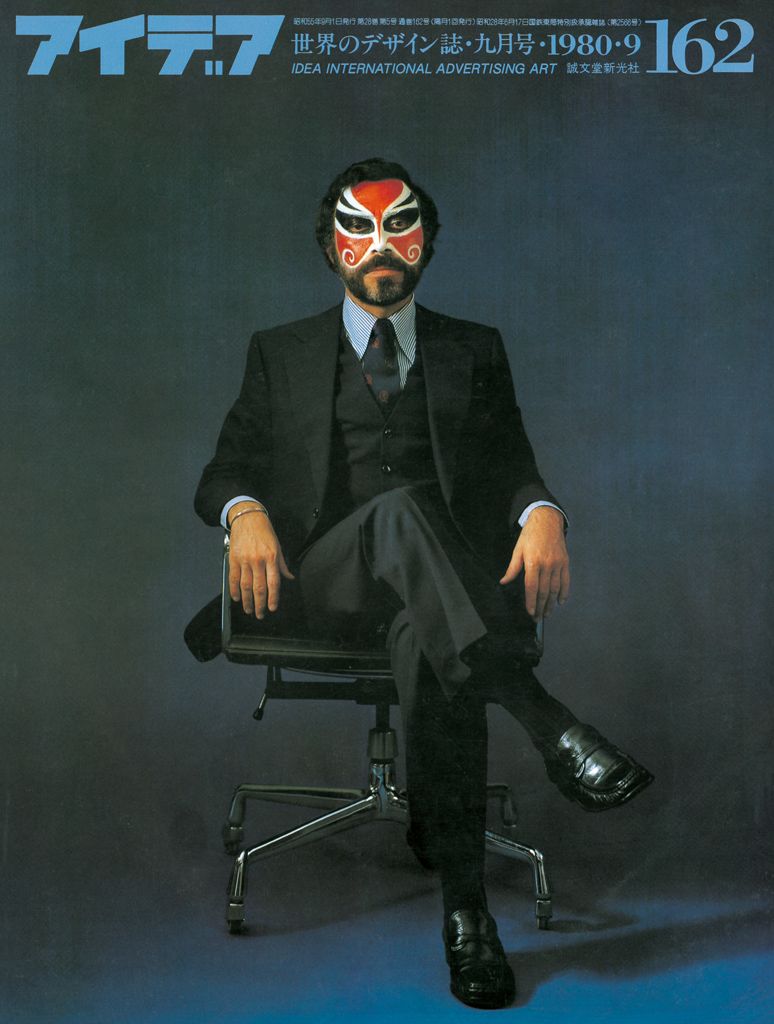
另外被石汉瑞放在林呱正在作画的画板上的那件作品其实也特别有意思。这是石汉瑞设计的一期《IDEA》杂志的封面,这个封面上是他西装革履地坐在一张椅子上,可是脸上却画着一张京剧的脸谱。这个设计本身就蛮有“自画像”的意味,作为一个外国人的他远渡重洋来到香港从事设计工作,面对的客户有中国人也有外国人,在这样一个多元的文化环境中工作,正如画着京剧脸谱的他,体现了他对多元文化的包容。
其实石汉瑞这种“中和一切”的能力到了现在也非常的值得我们学习。张亚东在《圆桌派》中说过现在是一个拼贴的时代,其实我觉得音乐和设计一样,对设计来讲这同样是一个拼贴的时代,没有什么是不能够放在一起的,只要能将两个或者是多个不同的东西巧妙地“中和”在一起,那么就是一个好的创意。可是到底应该怎么样“中和”呢?这就是值得我们去探究和学习的地方,下面我们来看看石汉瑞是怎么“中和”一切的?
图像的中和
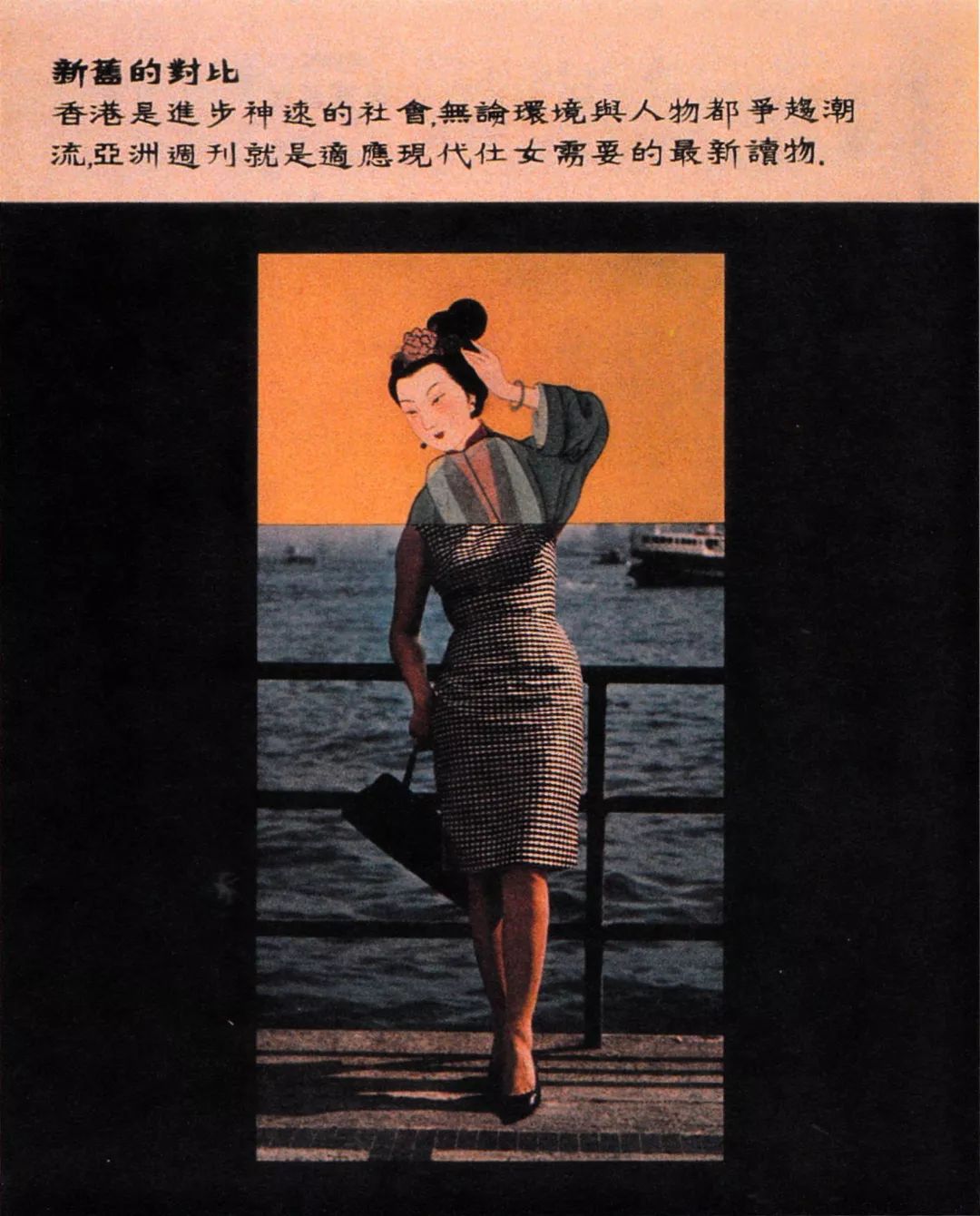
1964年,《亚洲周刊》为了想突出杂志的前卫和新颖,设定了一个“新旧的对比”主题。石汉瑞用两个完全不同的女性上下组合而成的一个新形象作为主体画面。一个是古代的仕女,一个是背对着香港天星码头的现代摩登女性,通过古与今的两位女士作对比,来强调“新旧的对比”。另外从面积上看,上面的古代仕女所占的面积小于下面的现代女性,从而突出强调“新”的力量。虽然是机械的切割,但是通过位置和大小的合理摆放,使得新形象看上去自然、协调,没有违和感。
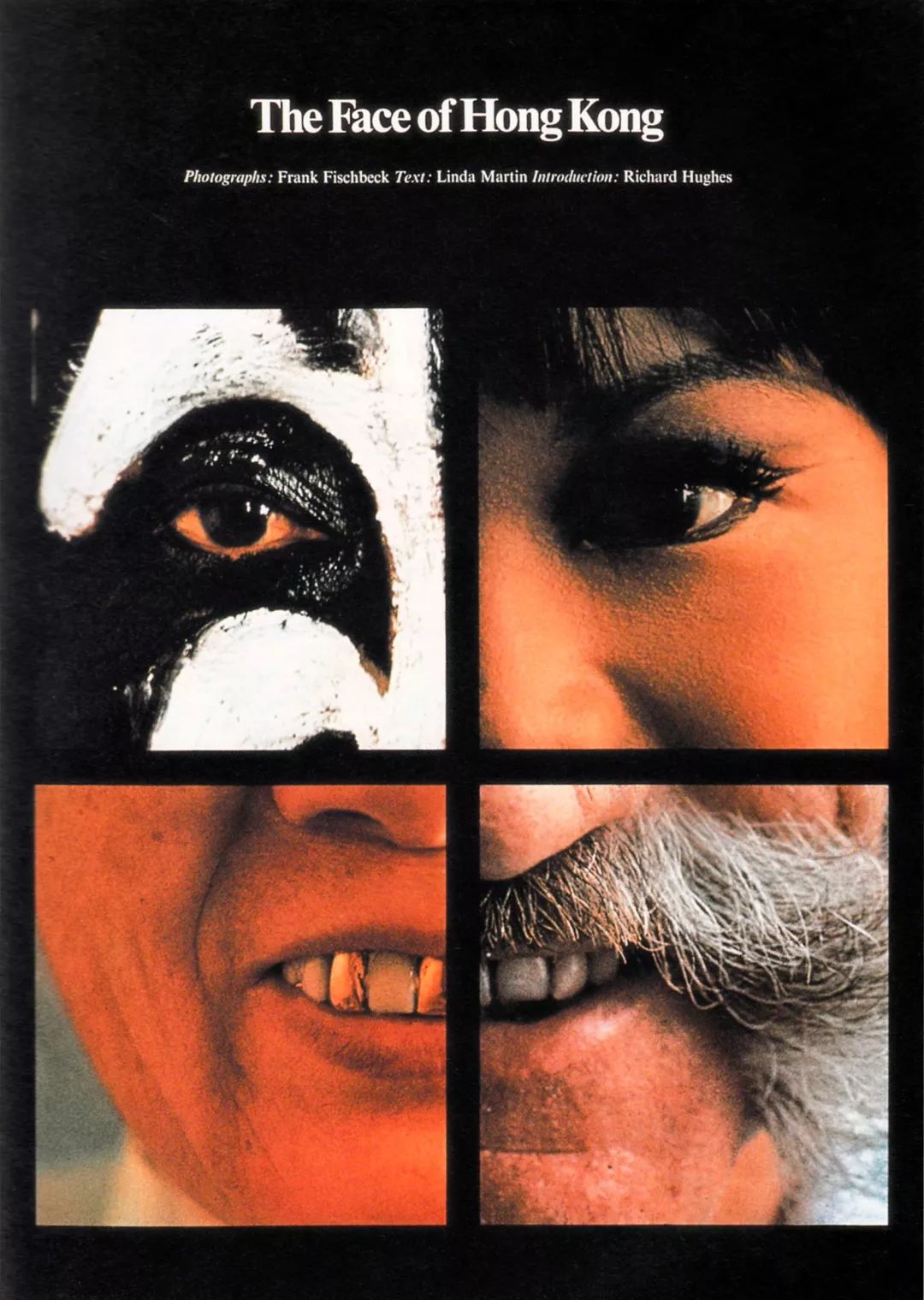
《香港面貌》是一本展现香港人面貌的摄影画册,画册里呈现了28组不同人物的肖像摄影,不同年龄不同职业,每一组人物形象都代表着香港生活的一个方面。石汉瑞在设计这个画册封面的时候,选取了4个身份不同的人物肖像,分别是粤剧演员、酒吧女郎、镶了金牙的阿嫲和在天星码头工作的外国人,各取其脸部形象的四分之一然后重新组合成一张新的面孔。这个设计一方面与画册展示人物肖像的主题相呼应,另一方面也简洁明了地将香港多元文化共处的特点表达了出来。
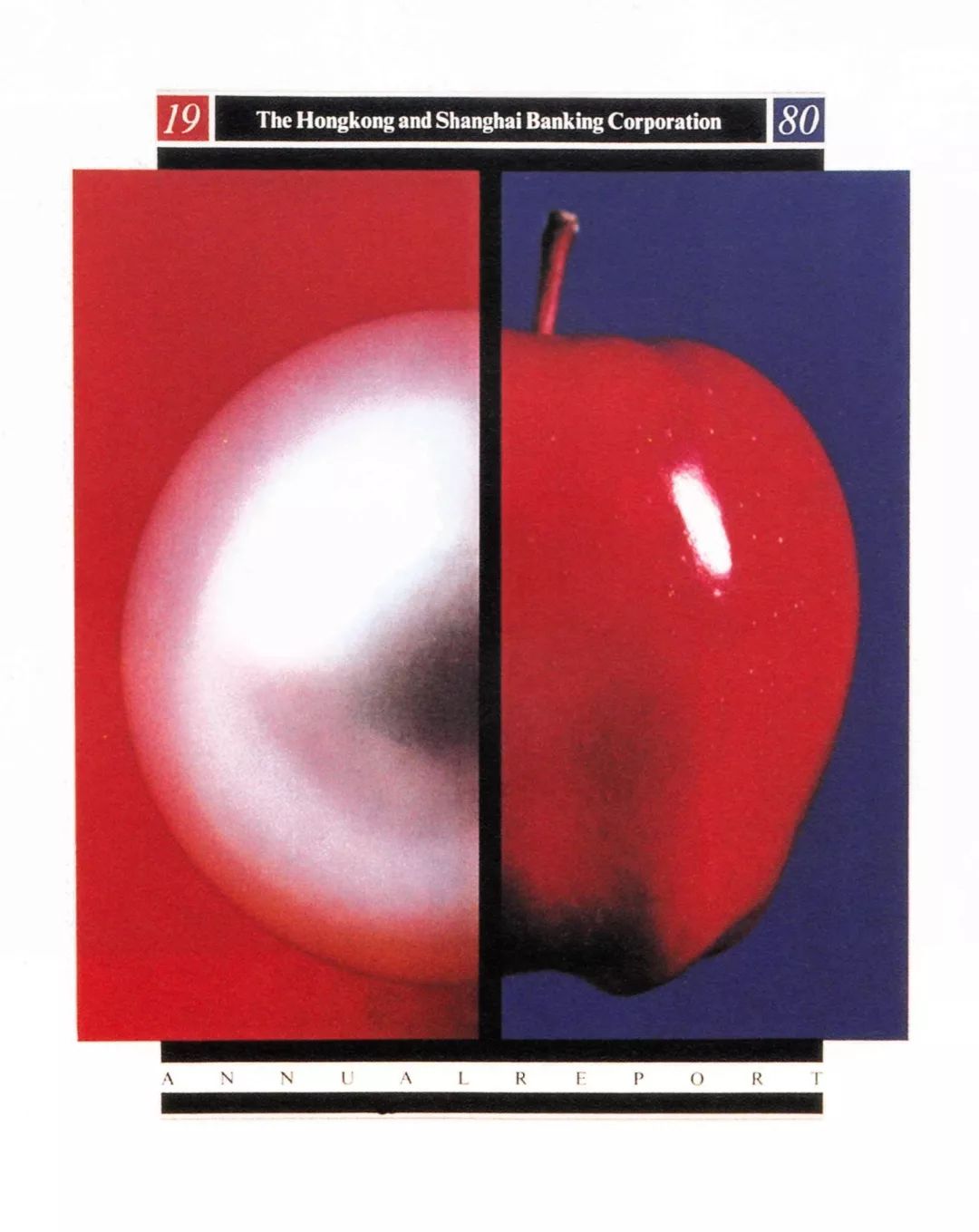
1980年,石汉瑞为汇丰银行纽约分部成立100周年设计年报,在年报的封面中,石汉瑞同样使用了图像分割再重新组合的手法。石汉瑞选用了珍珠代表被称作“东方明珠”的香港,选用苹果代表“The Big Apple”纽约。各取左右一半并置在一起,表明了香港汇丰银行和纽约分部的隶属关系。
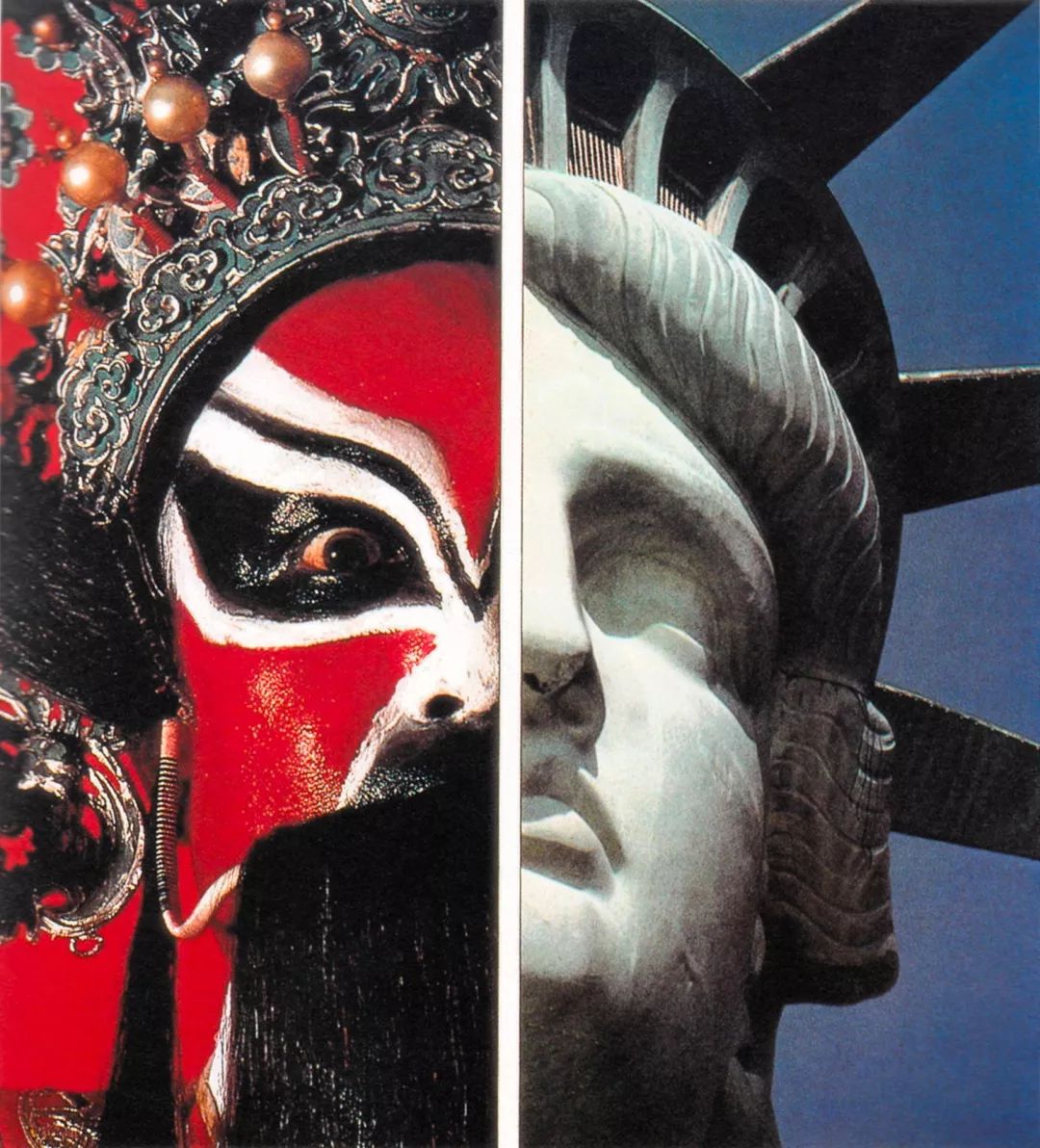
在该年报的内页中也有一页用了相同的方法,将粤剧的人物形象与纽约自由女神像各取一半然后并置一起。20世纪80年代是香港经济飞速发展的时期,将香港和纽约放在一起,体现了汇丰银行全球化扩张的战略和预示着香港的发展前景。
文字的中和
为了突出《亚洲周刊》的前卫与新颖,石汉瑞为其做了一个不同文字进行对比的海报。画面的主体由红色的黑体字“新”和绿色的书法字“旧”组成,这两个字被45°斜线切割去掉了一半,然后并置在了一起。石汉瑞直接用文字的字义来表达“新”与“旧”的对比。另外,黑体字相较于传统书法字也算是新式的,黑体字机械整齐的线条与飘逸灵动的书法字也形成了视觉上的强烈对比。
1999年石汉瑞为《海平面》杂志设计了一期封面,这一期的主打内容正是关于石汉瑞的专访。石汉瑞用了一张紫色的纸片遮挡住了摩登女郎的脸。我们主要来看看这纸上的内容。纸片上由一个逆转的希伯来文字母和一块石头组成,希伯来文与石头的形状正好形成了汉字“石”字,“石”字是石汉瑞的中文姓氏,而希伯来文是犹太民族使用的语言,是石汉瑞的母语,代表了石汉瑞的犹太人身份。这是一个对希伯来文和汉字的中和创造。
跨文化的符号借用
石汉瑞给自己公司设计了一套12年的企业办公文具形象,每一年的形象都对应着当年的生肖属相,当时石汉瑞对这些生肖的设计并没有按照中国人对生肖的传统印象进行设计,而是借用了一些西方的文化元素,我们来看看两个例子。
兔年兔子的形象采用的是西方童话故事《爱丽丝梦游仙境》中的插图——一只衣着英伦服饰,手持怀表的兔子,将活在西方童话故事里的兔子带到了遥远的东方,引发了一场跨文化旅行。
鼠年的形象并非老鼠,而是一块残缺的奶酪,奶酪残缺部分的负空间组成了迪士尼的米老鼠形象,借用了美国的文化元素来体现中国的传统生肖。
为渣打银行设计的钞票可以算得上是石汉瑞的十分知名的一个设计了,在他设计的图案中,具有吉祥寓意的中国神话传说中的动物形象依据等级的高低被使用到了不同面额的钞票中,其中10元的对应鲤鱼,20元对应龟,50元对应狮子,100元对应麒麟,500元则放了凤凰,而最高面额的1000元则放了最高级的龙的形象。这些动物在中国文化中都是瑞祥的象征。从最低面额的鲤鱼,到最高面额的龙,正对应了“鲤鱼跃龙门”的说法。这样将中国传统的动物形象放在了现代的纸币上,做出了一个跨文化的,具有香港特色的纸币,也避免了不同面额上放不同人的肖像的尴尬。
在2010年,渣打银行更新了他们的钞票设计,这次的设计就更能体现跨文化的对比了。纸币的正面依然保留了吉祥瑞兽的使用,而背面则使用了代表传统历史文化的图案和代表现代新科技的图案。20元的纸币中使用的是中国计算工具算盘和电子计算机中的二进制代码;50元的是一把中国古锁和现代银行金库门;100元出现的是宋代篆刻印章和电子线路板;500块的则是民间面相图和反映现代生物面部识别技术的图像;最高面额的1000元则是唐代铜钱和智能芯片。这样一新一旧的图案一前一后的出现,每一组都体现出了科技与文化遗产的主题。
在这里举一个反面的例子吧,去年香港金管局联合渣打、汇丰和中国银行(香港)三间发钞行推出2018香港新钞票系列,三大发钞银行首次统一了五大背面设计主题,分别用了饮茶文化、蝴蝶、粤剧、六角岩柱和金融都会放在20、50、100、500、1000元的钞票上。
石汉瑞认为这次钞票的五个主题并不能反映香港价值,记者访问他的看法时,他嘲讽地反问记者:「蝴蝶可以象征香港价值?即使可以,但在一些国家,蝴蝶象征爱玩女人的男人。粤剧也不是今日香港的标志,它不是香港的能量。当我想到香港,我会想到普罗大众做各种各样的事,如在公园耍太极,但不是在台上表演的人。」
石汉瑞又狠评新钞票的美学,他尤其看不透中国银行的一千元钞票:「一个做了开脑手术的头颅,然后里面全都是钱?我觉得……这实在太有趣了。但有趣的钞票未必是一件好事──它可以让人留下深刻印象,但同时也要有庄严感(sense of dignity)。像人民币印上毛泽东的人像,就有庄严感。」
图像与文字的中和
八卦图是石汉瑞最喜欢的图形,因为它永远处于一种平衡的状态,这种平衡是动感的平衡,是万物和谐相生的平衡。1989年石汉瑞为韩国双龙集团(Ssangyong)设计的企业标志便是借鉴了八卦的图形。该标志由企业名称的首字母,两个英文的“S”前后组合而成,两个“S”是通过中心对称的。这种位置关系的处理,加上两种颜色的搭配,是标志可单独识别为两个部分,又可组合为统一整体。
这一个邀请卡的设计是在纽约历史协会举办的有关玩具的展览,画面的主形象同样是采用手绘插画与实物照片结合的形式结合。动物形态玩具车的头、四肢和轮子都是以手绘的形式出现,而身体部分则被众多的堆叠在一起的看图识字的圆形卡片替代,这些圆形卡片是上印着的是各种玩具的图像,其中印有“TOYS”的卡片被放在了最显眼的位置,点明玩具展的主题。
随着时代的发展与进步,我们将面对越来越多的外来文化。面对这些外来文化,我们将如何取舍,我们又应该怎么样去捍卫我们本土的优秀文化,石汉瑞或许已经给我们做出了一个很好的榜样,真正的“中和”设计并不需要舍弃任何一边,而是能保留不同文化的特点的结合。希望今天的文章能够对你有所帮助,我们下期再见!